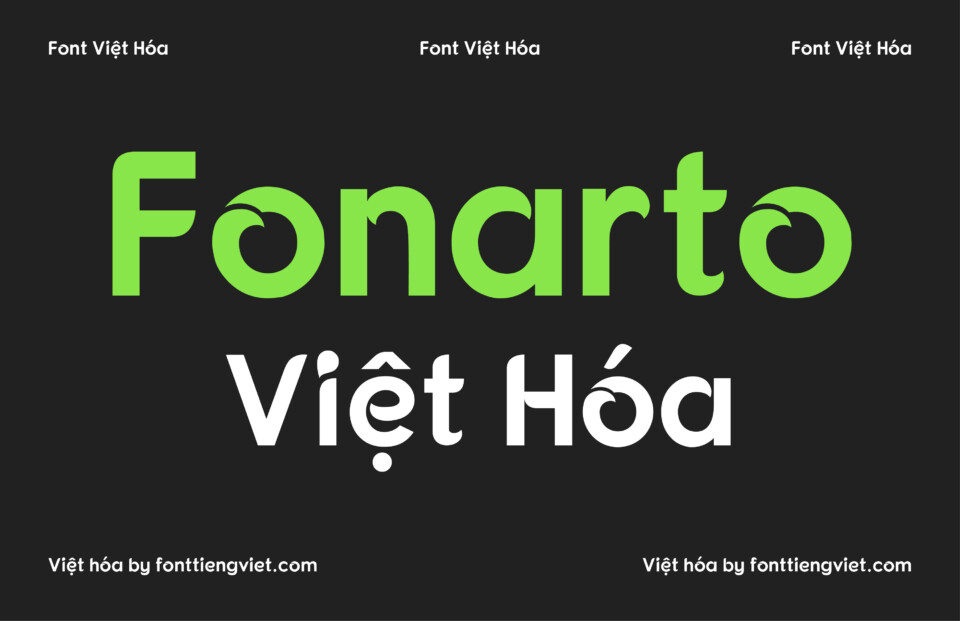
Font Việt hóa 1FTV VIP Fonarto
Font Việt hóa 1FTV VIP Fonarto – Lựa chọn hoàn hảo cho thiết kế đồ họa chuyên nghiệp
Trong thế giới thiết kế sáng tạo hiện nay, việc lựa chọn một bộ Font Việt hóa 1FTV VIP Fonarto chất lượng đóng vai trò vô cùng quan trọng để tạo nên những tác phẩm ấn tượng. Font Miễn Phí luôn là mục tiêu tìm kiếm hàng đầu của các bạn học sinh, sinh viên và những nhà thiết kế trẻ đang bắt đầu hành trình nghệ thuật của mình. Fonarto không chỉ đơn thuần là một kiểu chữ, mà còn là sự kết hợp tinh tế giữa phong cách cổ điển và hơi thở hiện đại, giúp thông điệp của bạn trở nên sống động hơn bao giờ hết. Với phiên bản đã được 1FTV Việt hóa kỹ lưỡng, người dùng tại Việt Nam giờ đây có thể thoải mái sử dụng mà không lo lỗi font khi gõ tiếng Việt có dấu, giúp quy trình làm việc trở nên trơn tru và chuyên nghiệp hơn rất nhiều.
Đặc điểm nổi bật của bộ Font Việt hóa 1FTV VIP Fonarto
Phong cách thiết kế Sans-serif độc đáo
Bộ Font Việt hóa 1FTV VIP Fonarto thuộc họ chữ không chân (sans-serif) nhưng lại mang trong mình những đường nét biến tấu vô cùng sáng tạo. Các ký tự được thiết kế với độ dày vừa phải, tạo cảm giác thanh thoát nhưng vẫn đảm bảo sự chắc chắn và mạnh mẽ. Điểm đặc biệt của Fonarto chính là những góc bo tròn mềm mại kết hợp với các đường cắt sắc sảo, mang lại một tổng thể hài hòa và độc đáo. Đây là lựa chọn lý tưởng cho những ai muốn tìm kiếm sự khác biệt cho các tiêu đề lớn, banner quảng cáo hay các thiết kế áo lớp, logo trường học mang tính nhận diện cao.
Khả năng hiển thị đa dụng trên nhiều nền tảng
Dù bạn đang thực hiện một bài thuyết trình PowerPoint, thiết kế poster cho câu lạc bộ hay làm video cho mạng xã hội, Font Việt hóa 1FTV VIP Fonarto luôn đáp ứng tốt khả năng hiển thị. Nhờ cấu trúc chữ rõ ràng, font này giúp người xem dễ dàng tiếp nhận nội dung ngay cả ở khoảng cách xa hoặc trên các màn hình di động nhỏ. Việc được tối ưu hóa bảng mã Unicode giúp bộ chữ này tương thích hoàn hảo với các phần mềm đồ họa phổ biến như Adobe Photoshop, Illustrator hay thậm chí là các ứng dụng văn phòng cơ bản như Word và Excel.
Ứng dụng thực tế của Font Việt hóa 1FTV VIP Fonarto trong học tập
Thiết kế tài liệu và báo cáo sáng tạo
Đối với học sinh và giáo viên, việc sử dụng Font Việt hóa 1FTV VIP Fonarto giúp các trang bìa báo cáo, tập san hay bảng tin trường học trở nên thu hút hơn. Thay vì sử dụng những kiểu chữ mặc định nhàm chán, một chút thay đổi với Fonarto sẽ giúp nội dung giáo dục trở nên gần gũi và thú vị hơn. Các bạn học sinh có thể dùng font này để làm nổi bật các từ khóa chính, tiêu đề chương hoặc các trích dẫn quan trọng trong bài làm của mình, từ đó tạo ấn tượng tốt với thầy cô và bạn bè về sự chỉn chu và gu thẩm mỹ tốt.
Phát triển kỹ năng đồ họa cơ bản
Sử dụng các bộ font Việt hóa chất lượng như Fonarto cũng là cách để các bạn trẻ tập làm quen với tư duy thiết kế. Việc hiểu cách sắp xếp bố cục, khoảng cách dòng và lựa chọn font chữ phù hợp với ngữ cảnh sẽ đặt nền móng vững chắc cho những ai muốn theo đuổi ngành đồ họa chuyên nghiệp. Font Việt hóa 1FTV VIP Fonarto cung cấp một trải nghiệm thị giác tốt, giúp người dùng hiểu rõ hơn về giá trị của chữ viết trong việc truyền tải cảm xúc và thông tin đến người xem một cách hiệu quả nhất.
Kết luận về bộ font chữ ấn tượng này